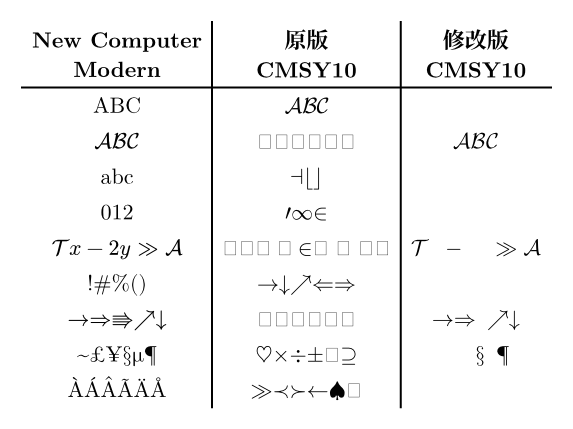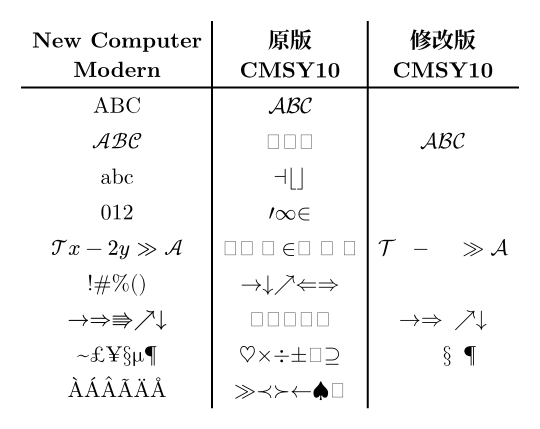
怎么把 cal 字体变成 LaTeX 里 mathcal 默认的那种?
✅ Typst 0.15 已变化
#8164 将 New Computer Modern 字体的版本更新到了 8.0.0。新版字体修改了 cal 的设计,现在与 LaTeX \mathcal默认设计一致了。
当前默认 $cal(K M Z), cal(P)_n, cal(T)^p$
旧版设计 $cal(K M Z), cal(P)_n, cal(T)^p$
如需恢复旧版设计,可设置stylistic-set: 6,详见 0.15.0 更新说明。
Typst 中数学字体默认是 New Computer Modern Math,与 LaTeX 中默认[1]的 Computer Modern Math 略有不同。
若想使用 LaTeX 默认的\mathcal花体,请按以下两种方法之一更换字体。
另外,LaTeX 中有 calligraphic 和 script 两种花体,此处是前者;后者请参考如何实现\mathscr的花体符号。
法一:使用修改版字体(推荐)
修改前 $cal(K M Z), cal(P)_n, cal(T)^p$
修改后 $cal(K M Z), cal(P)_n, cal(T)^p$
为何正则表达式如此凌乱?
以上正则表达式[𝒜ℬ𝒞𝒟ℰℱ𝒢ℋℐ𝒥𝒦ℒℳ𝒩-𝒬ℛ𝒮-𝒵]不可简省为[𝒜-𝒵]。由于历史原因,大写花体字母的编码并不连续,而分散在 Letterlike Symbols 和 Mathematical Alphanumeric Symbols 两块。具体可参考 typst/codex 源代码或 Mathematical Alphanumeric Symbols - Wikipedia。
需要同时使用 scr?
以上设置会同时影响cal(A)和scr(A),因为 Unicode 把它们统一编码了[2]。
如需同时使用二者,请自定义函数设置字体。
默认字体效果 $cal(L)^p != scr(L)^p, cal(a)_n = scr(a)_n$
更换字体之后 $cal(L)^p = scr(L)^p, cal(a)_n = scr(a)_n$
自定义`scr`后 $cal(L)^p != scr(L)^p, cal(a)_n = scr(a)_n$
只自定义`cal`也可行 $cal(L)^p != scr(L)^p, cal(a)_n = scr(a)_n$
法二:使用原版字体
font: "cmsy10"并用upright切换到普通码位
为何出现 matplotlib?
Computer Modern Math 早于 OpenType 技术标准,通常以 Type 1 字体形式存在,如cmsy10.pfm。
今天很多软件都不支持*.pfm。matplotlib 开发者将它转换成了cmsy10.ttf,可供 Typst 等软件使用。
该方法存在以下若干问题,主要为介绍原理而保留;法一通过修改字体解决了这些问题,实用时还是推荐法一。
上下标位置不对
cmsy10.ttf缺少 MathKernInfo 等信息,导致上下标位置异常。其中,竖直位置有玄学办法勉强修补(加上context),而水平位置则无已知办法能完全解决。
正常效果 $cal(P)_n, cal(T)^p$
异常效果 $cal(P)_n, cal(T)^p$
勉强修补后 $cal(P)_n, cal(T)^p$
更全面的测试请参考 How to use (old) Computer Modern for math.cal? And why context matters? - Questions - Typst Forum。
码位不是数学字符
该方法中,大写字母复制出来是KMZ(ASCII)而非𝒦︀ℳ︀𝒵(Unicode 数学字符),而其余字符更是连显示也不对。这是因为原版cmsy10.ttf设置的码位不符合今日习惯,如对比表格所示。
对比表格
上例出现警告是正常现象。